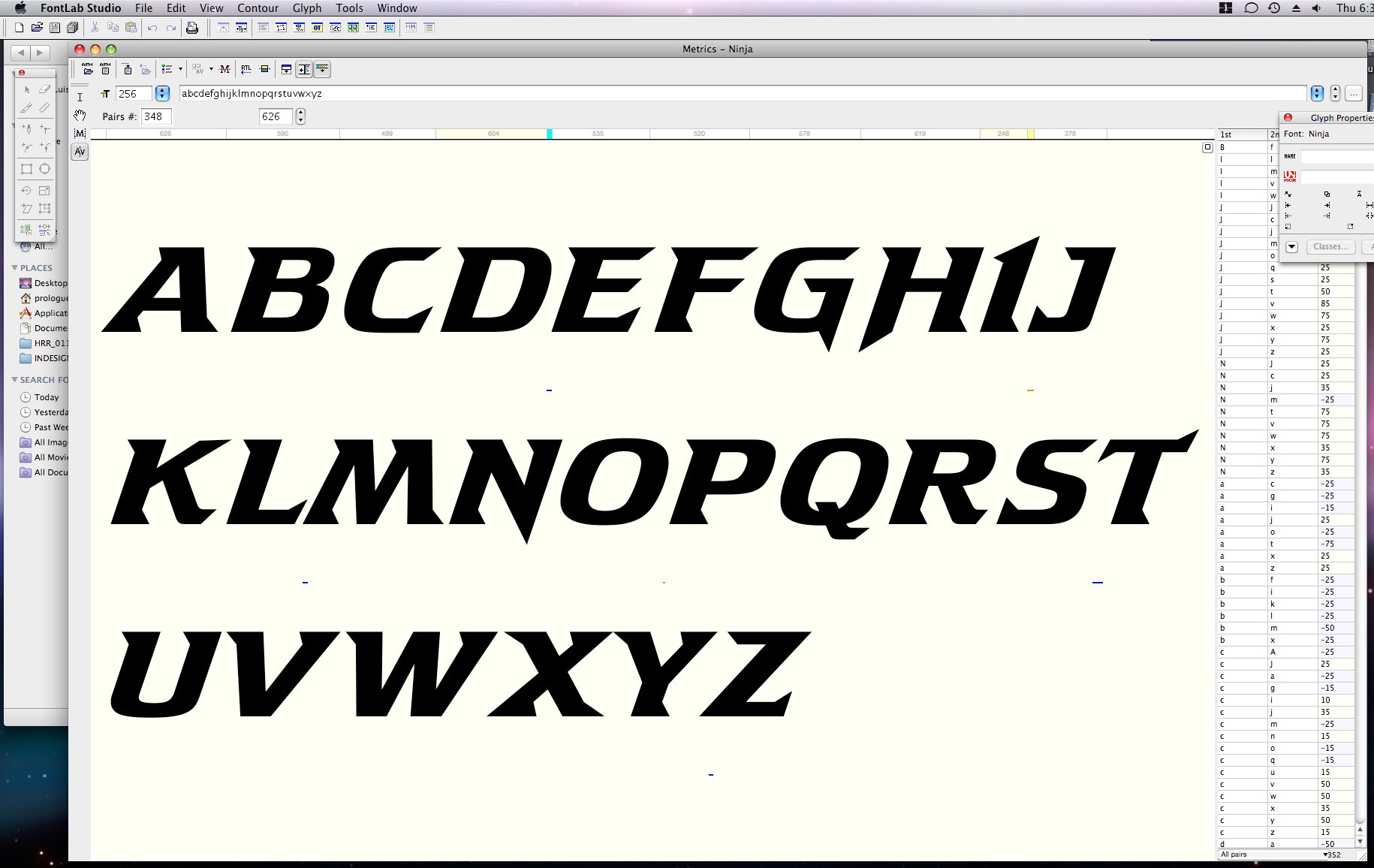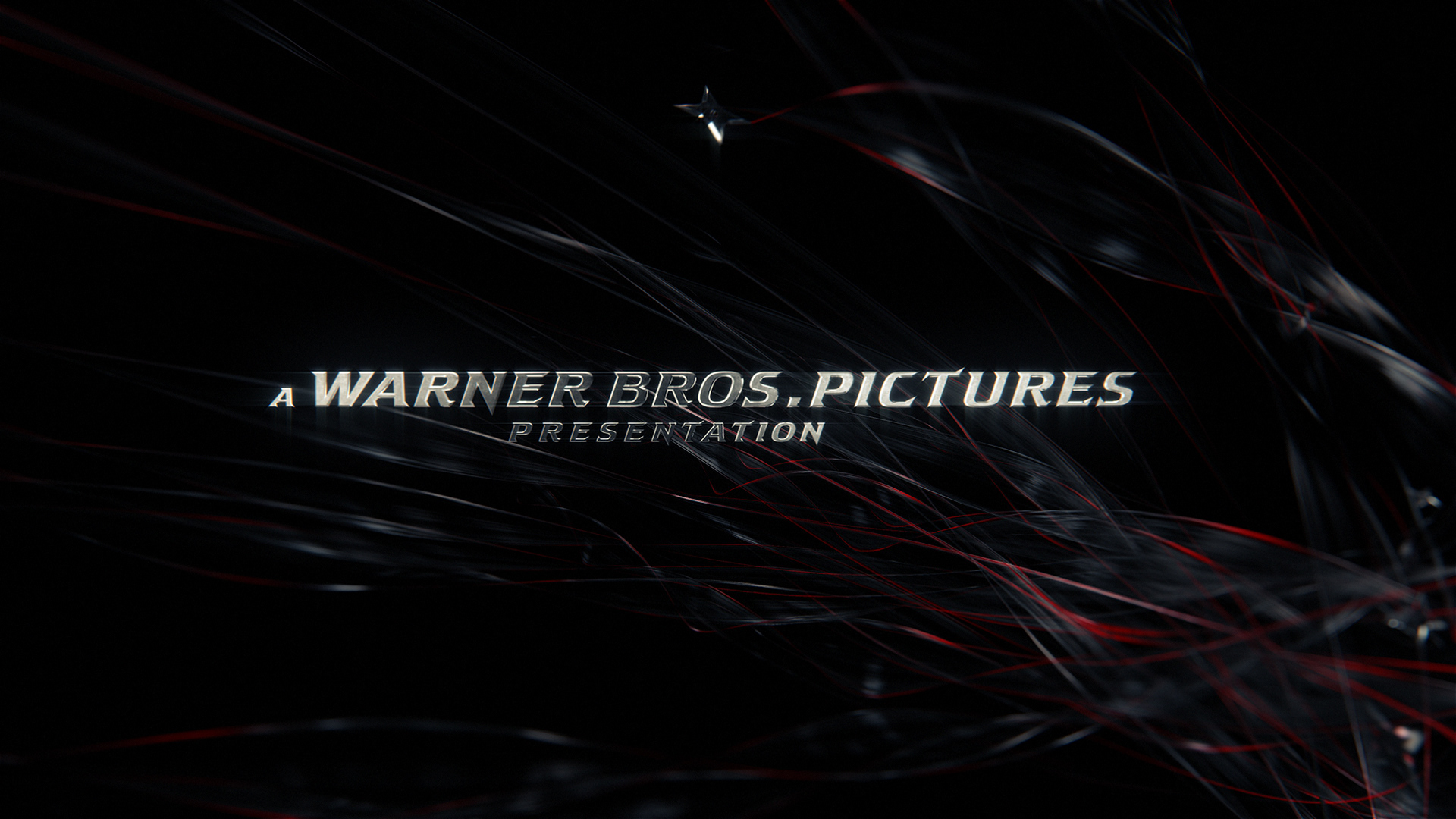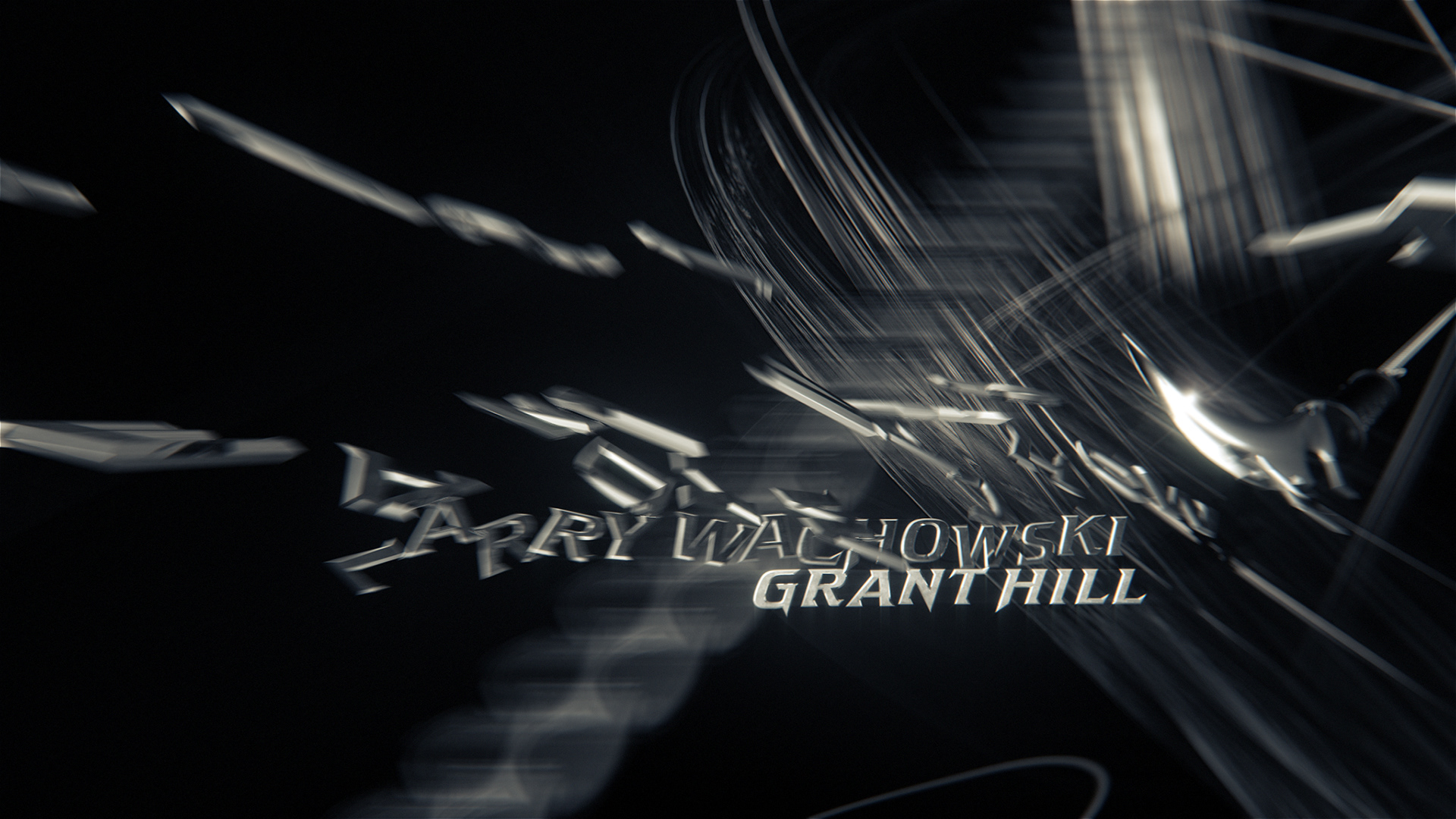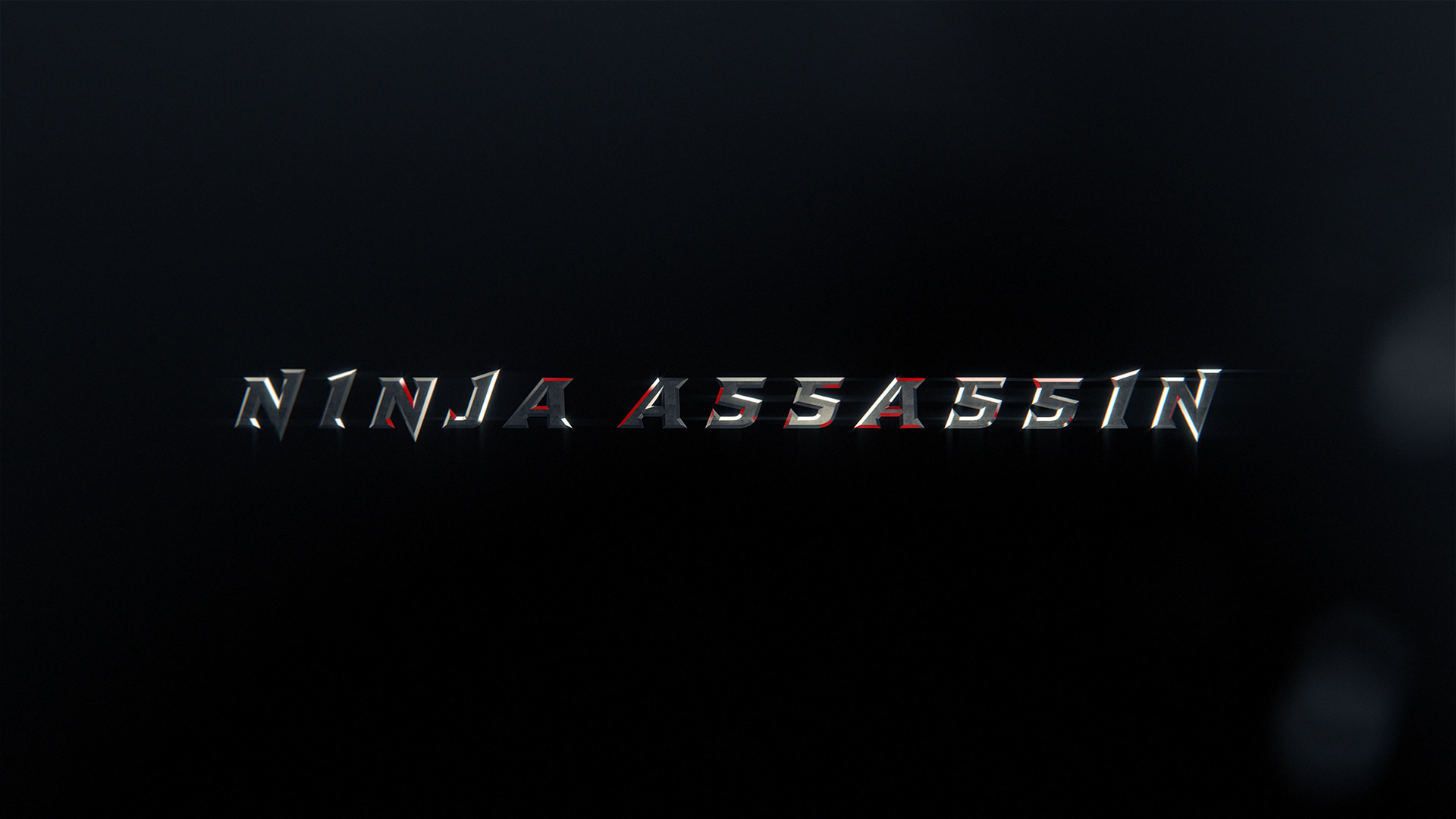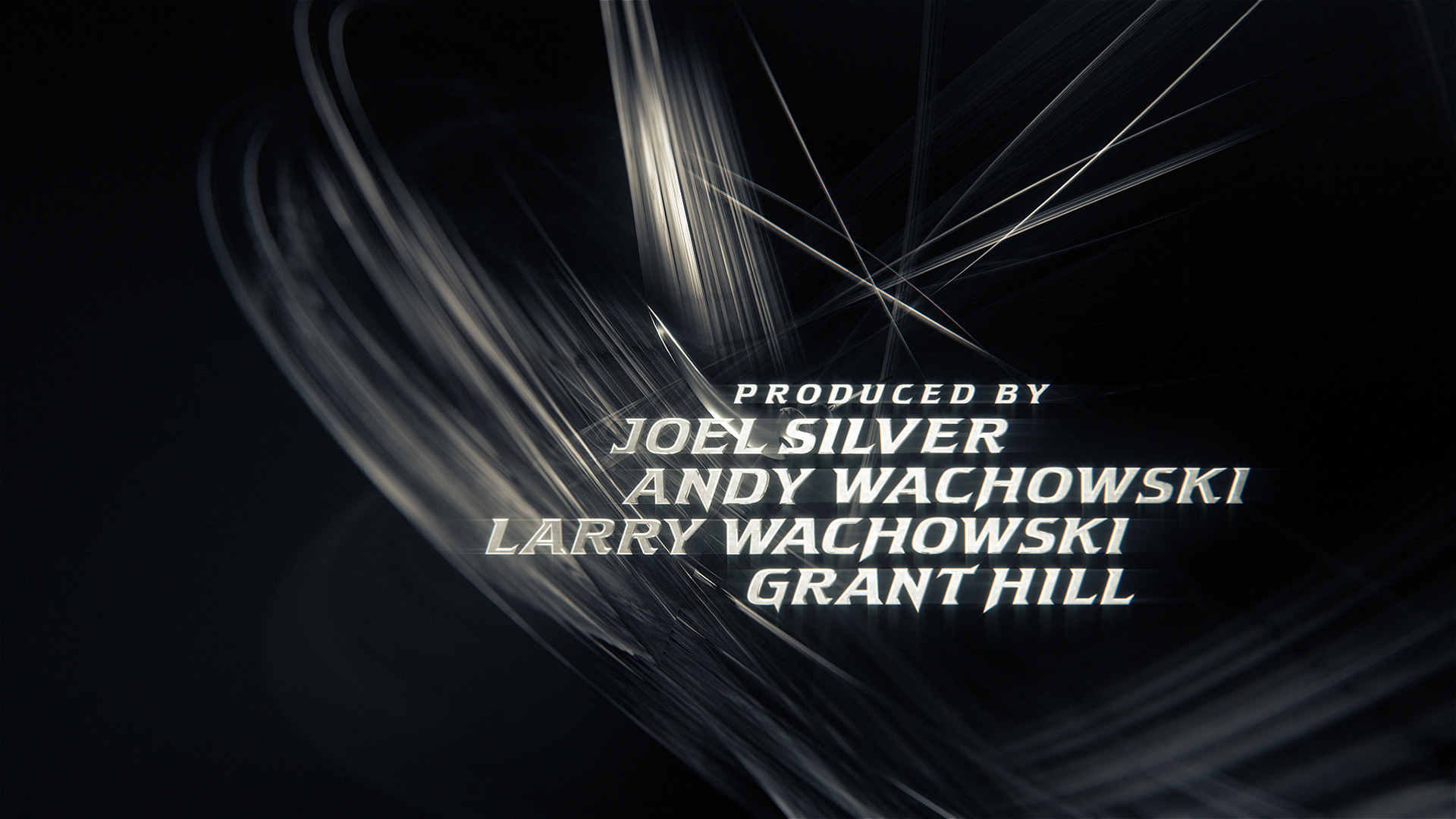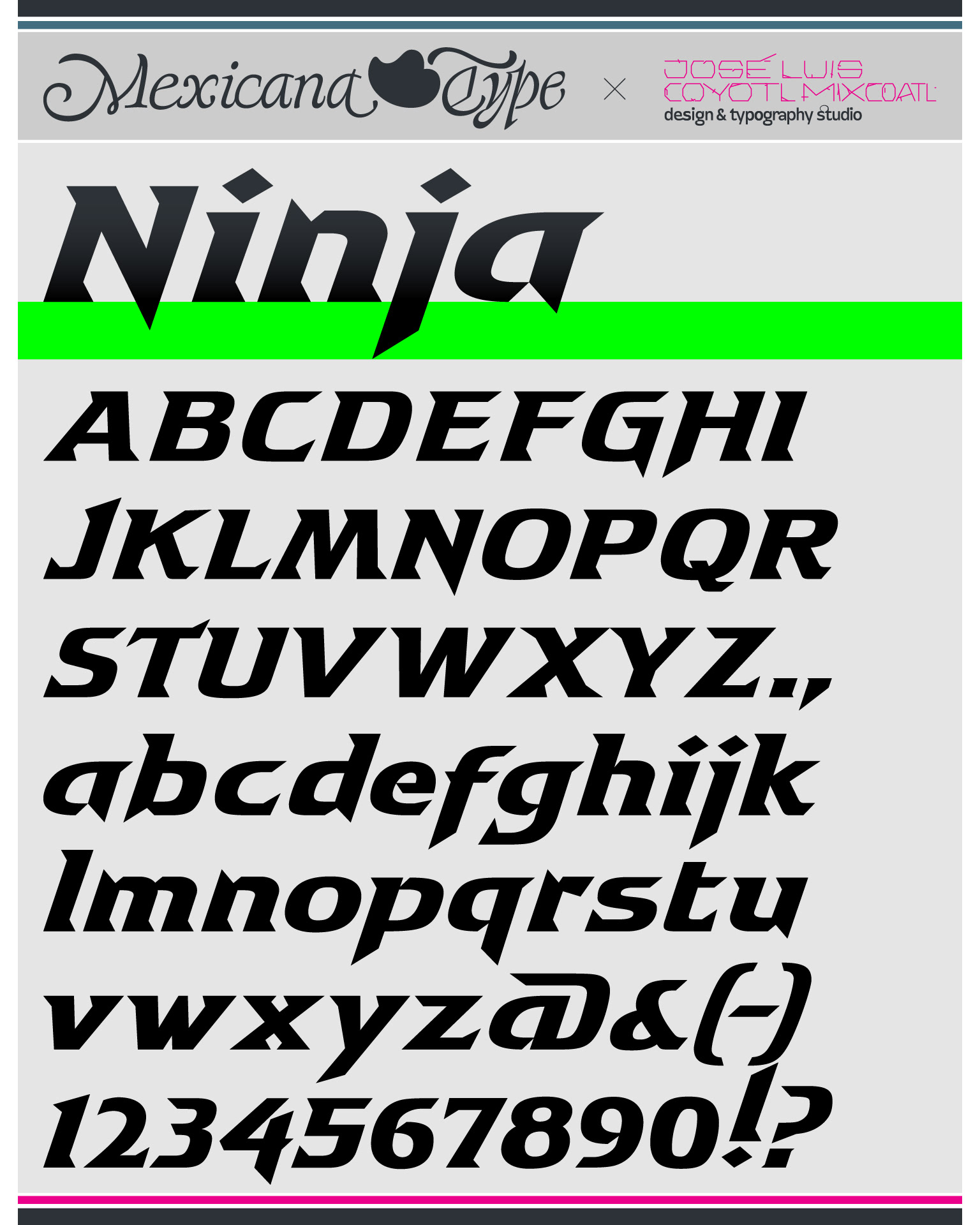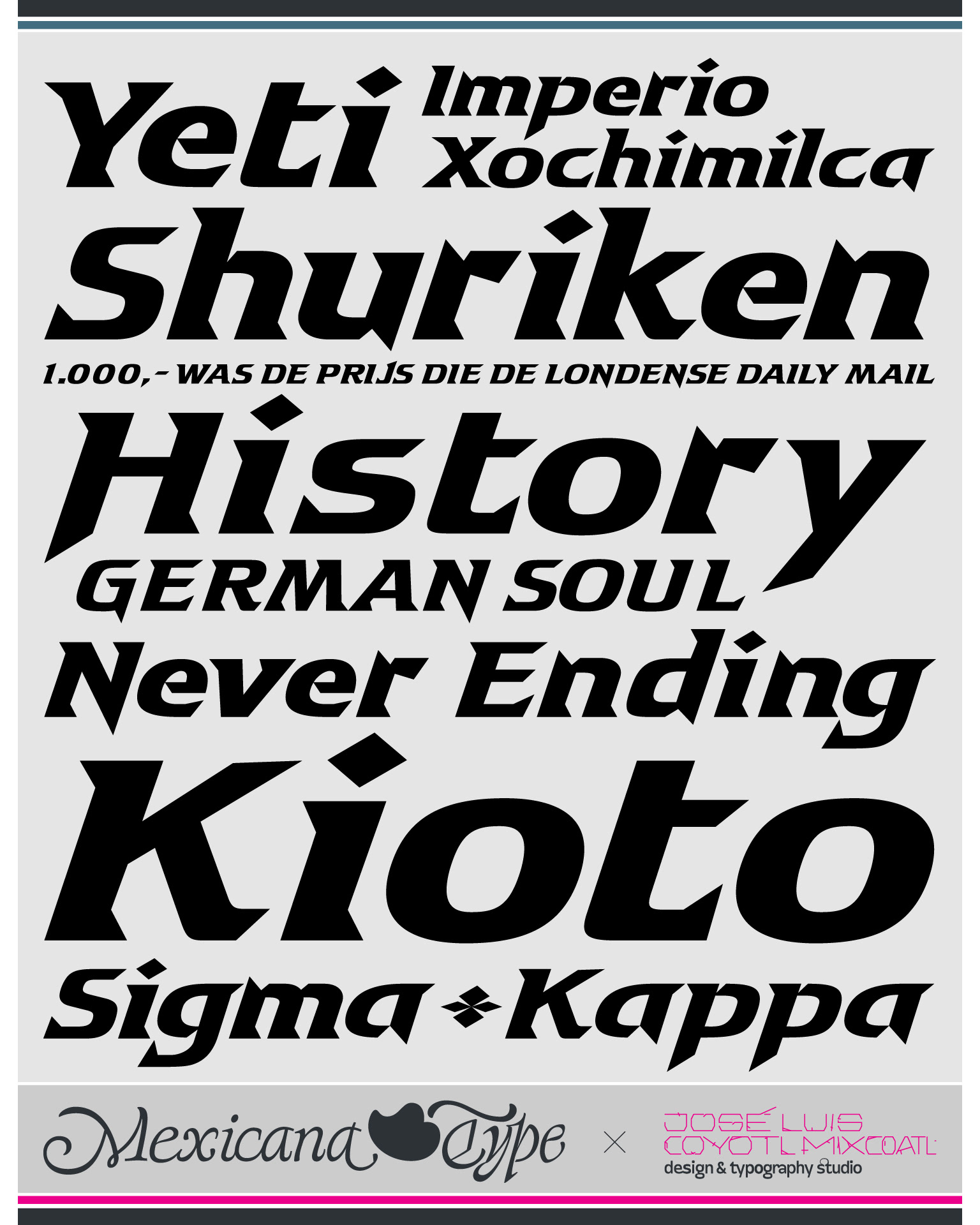
Ninja Assassin
Ninja fue una tipografía personalizada diseñada para el paquete de créditos (Título principal, locators, créditos finales, endcrawl y también para fines de marketing) de la película Ninja Assassin, dirigido por James McTeigue y producido por los Hermanos Wachowski (The Matrix Trilogy).
Ninja fue diseñada junto con el talentoso director creativo Heebok Lee en Prologue Films.
Fue concebida como custom type originalmente para los textos de la secuencia, una vez terminada el cliente solicitó la versión como fuente, lo que por supuesto no existía pues todo se había hecho desde el diagramado vectorial, de modo que se tuvo que hacer el archivo digital como custom font para necesidades de marketing, trailer, endcrawl, entre otros.